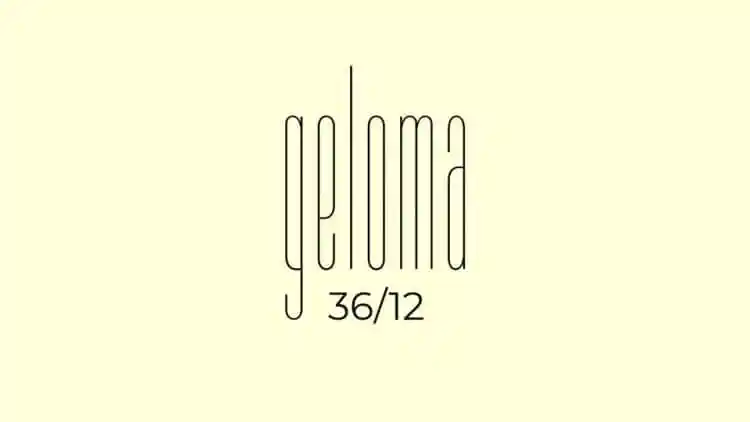
Geloma Display Font
Geloma Display Font é uma família de tipo sans-serif criada por Justin Penner que destaca-se pela sua estética única. As letras longas e finas remetem a fios na mandinga, um detalhe visual fascinante quando colocadas juntas. Foi desenvolvida para headlines, títulos e outros textos curtos de forma perfeita, sendo perfeitamente adequada a diversos usos como publicidade, mood boards vintage, marcações, logotipos, embalagens, design editorial e até mesmo arquitetura moderna e vintage. Suas linhas fluidas e elegantes permitem que o designer crie um estilo único e chamativo em qualquer projeto, tornando-o uma opção valiosa para aqueles buscando um toque distintivo em seus trabalhos visuais.